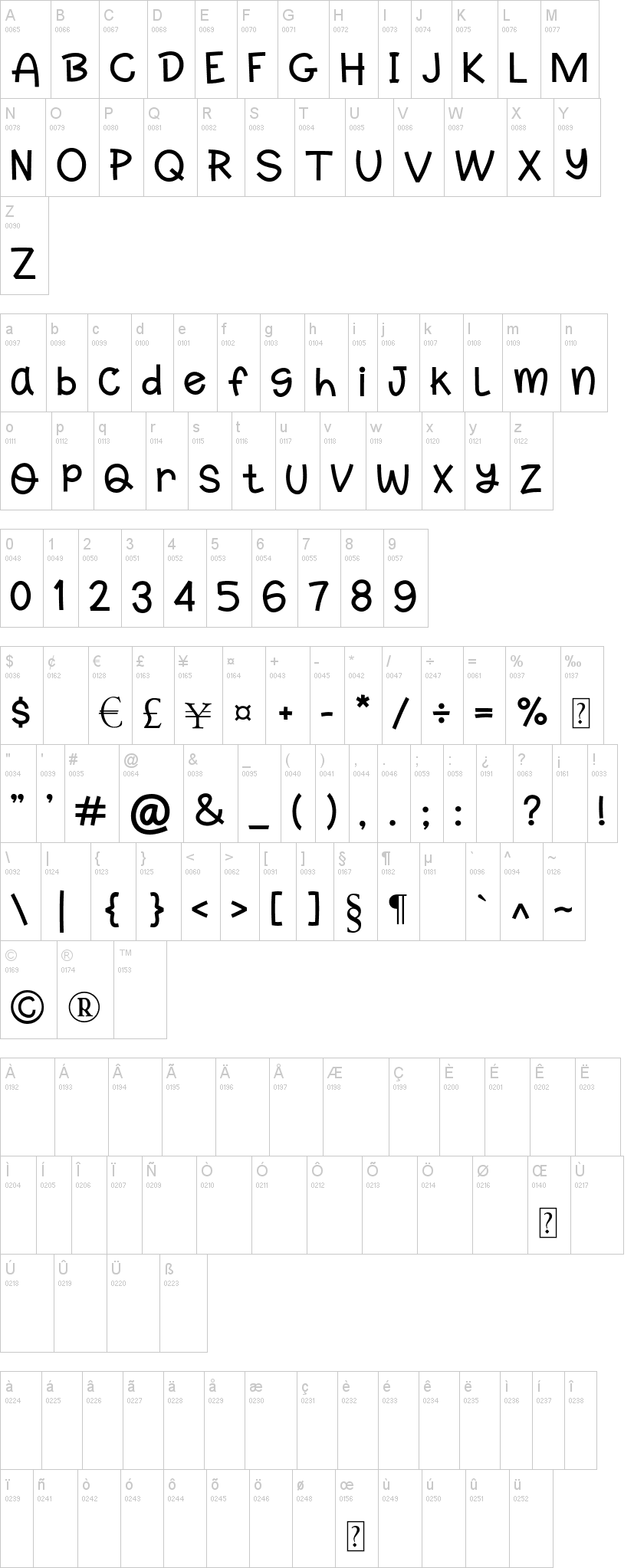
Lompo 字体是一款由设计师 Juan Hodgson 创作的开源字体,它的设计灵感来自于非洲的卢姆珀亚库(Lompong Yaku)部落的文化和艺术风格。该字体于2014年首次发布,现在可以在 Google Fonts 上免费下载和使用。 Lompo 字体拥有一种独特的手写风格,它的字母形状 经过简化,使其更易于阅读和识别。字母间距离较大,这使得它在小字号下也能保持清晰可读。此外,该字体还包括了一些特殊字符和符号,如货币符号和数学符号等。 总的来说,Lompo 字体是一款简单、易读、具有良好可读性和非常适合在印刷品和数字媒体上使用的字体。内容介绍
Lompo是一款非常不错的手写艺术字体,具有很好的视觉感,适合于文化类的宣传设计、商业类品牌的广告和产品包装设计以及个性化文字排版等较多场景。